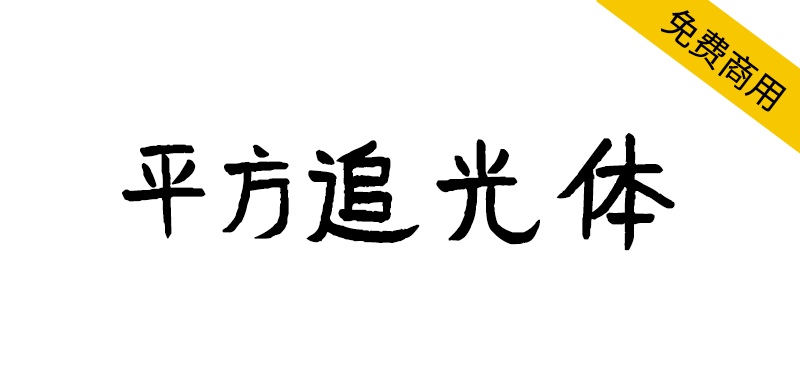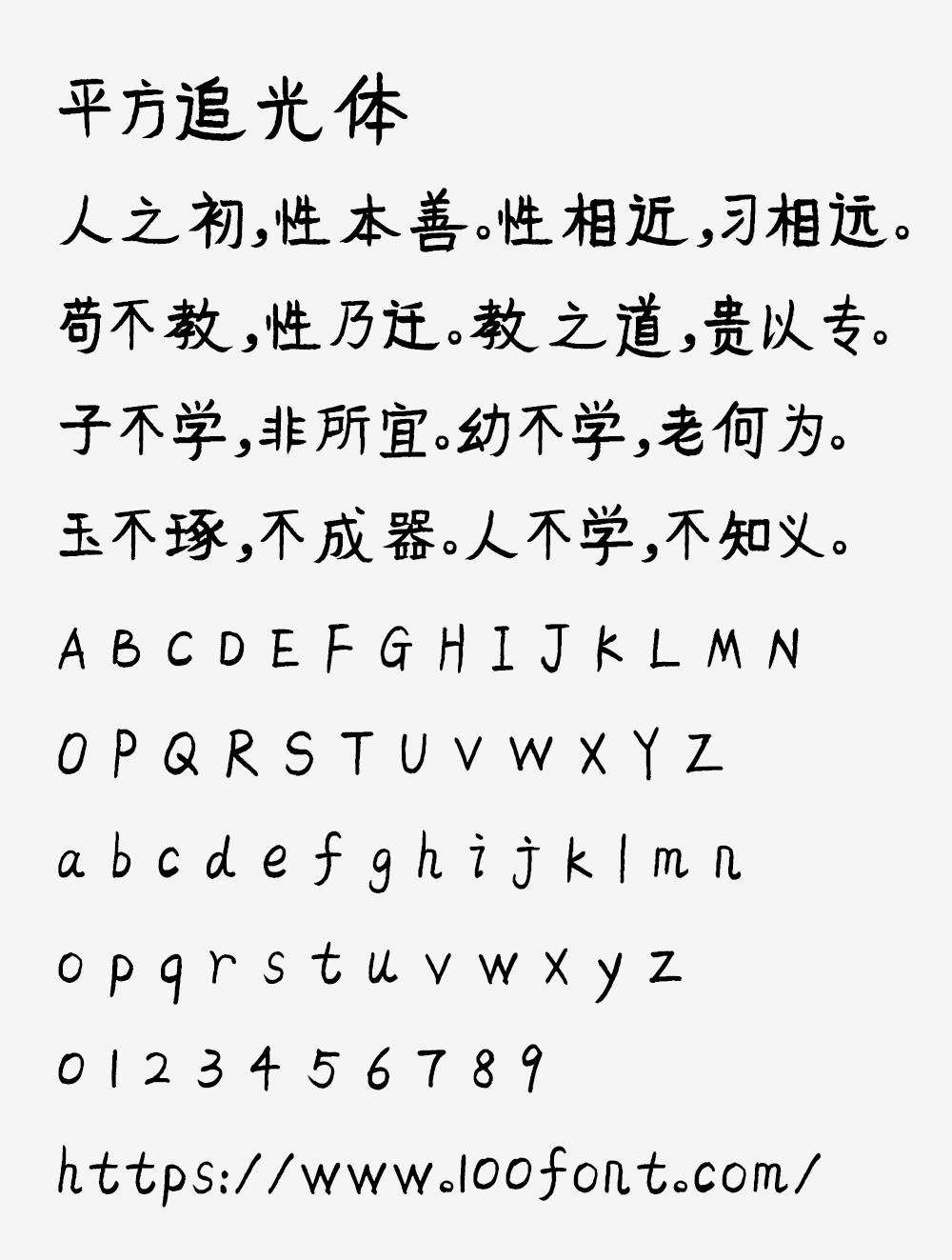
【平方追光体】一款具有手写艺术风格的创意字体
你是否在寻找一款既灵动又具艺术感的创意字体?平方追光体,以其自然的手写线条与独特的圆弧竖钩设计,瞬间提升设计作品的视觉温度。支持在线预览,免费商用无负担,广告、电商、自媒体皆宜。但注意:不可修改或用于商标嵌入。揭秘这款热门字体的背后使用规则与美学逻辑,让每一次用字都合规又出彩。
【平方追光体】一款具有手写艺术风格的创意字体
平方追光体是一款具有手写艺术风格的创意字体,其线条粗细变化自然,竖钩笔画融入圆弧设计元素,整体呈现灵动活泼的视觉效果,适用于各类设计需求。
【平方追光体】一款具有手写艺术风格的创意字体